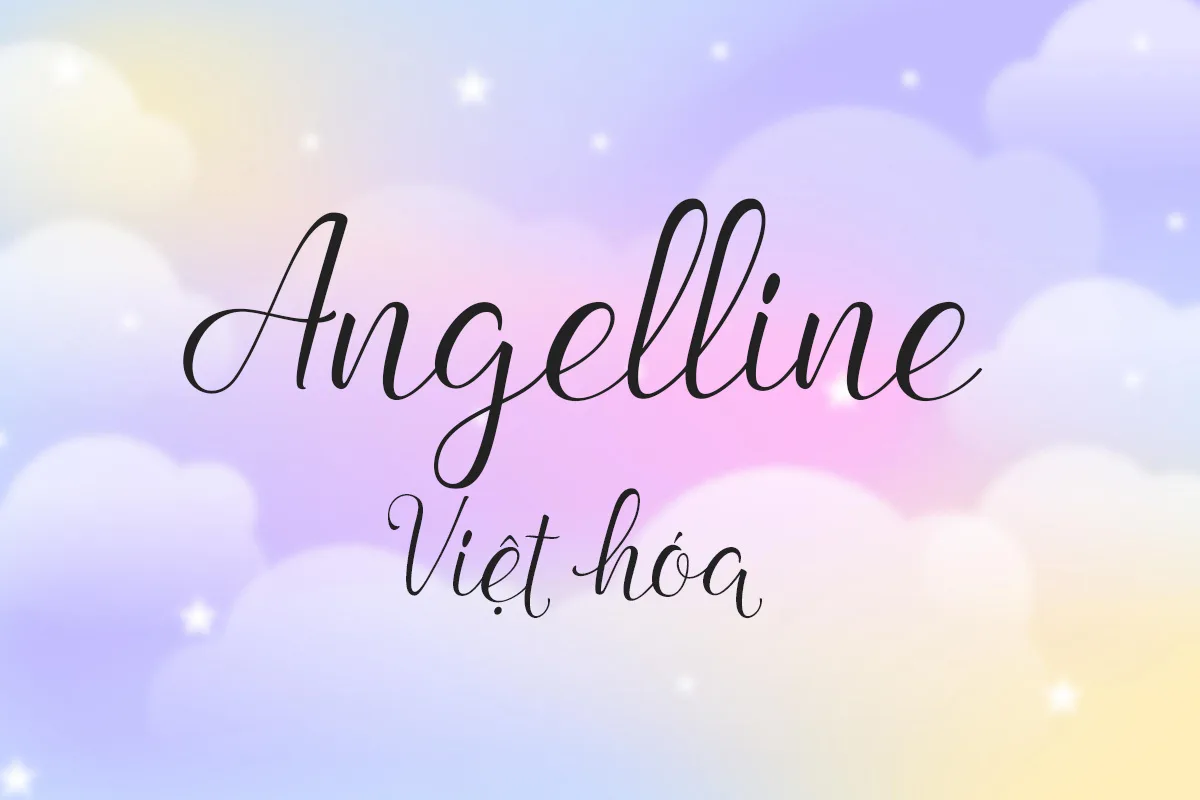
Angelline Việt hóa – Font viết tay ngọt ngào cho thiết kế lãng mạn
Angelline Việt hóa là một phông chữ script mang phong cách viết tay nhẹ nhàng, duyên dáng và đầy cảm xúc. Từng nét chữ được thiết kế mềm mại, uyển chuyển như những dòng viết tay thủ công, gợi liên tưởng đến sự lãng mạn, ngọt ngào trong từng thông điệp. Phông chữ này đặc biệt phù hợp với các thiết kế thiệp mời, nhật ký, bìa sách, sản phẩm thời trang, làm đẹp hoặc thương hiệu hướng đến phái nữ.
Bản Việt hóa được tối ưu hóa với đầy đủ dấu tiếng Việt, giữ nguyên phong cách thanh thoát của bản gốc mà không làm mất đi sự hài hòa tổng thể. Nếu bạn đang tìm một font chữ nhẹ nhàng, thơ mộng và dễ dùng trong các thiết kế mang cảm xúc, Angelline Việt hóa là lựa chọn lý tưởng.